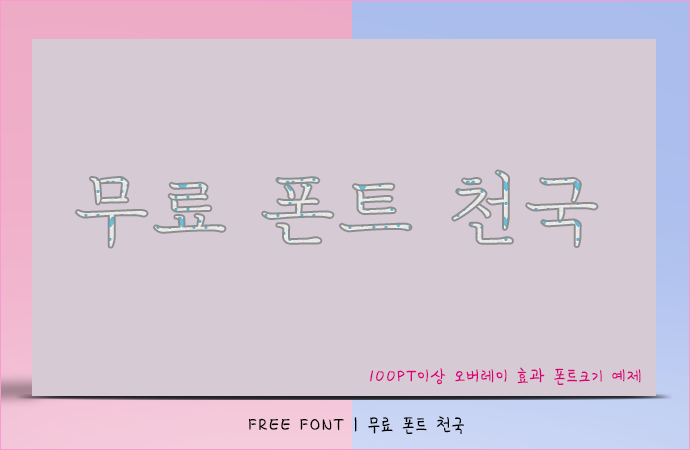
억새풀의 감성이 담겨 있는 마포 꽃섬 한글 폰트
마포 꽃섬 폰트 정보
마포 꽃섬은 난지, 하늘공원의 탁 트인 하늘과 살랑이는 억새풀의 감성적인 인상을 서체로 표현 했습니다. 길게 뻗은 획과 완만하게 구부러진 부리는 부드러운 식물의 줄기를 표현 했으며 획의 두께를 얇게 하고 획순에 따라 끊음으로써 부드럽고 따뜻한 인상을 주고 있습니다. 본 서체는 누구나 자유롭게 사용 가능한 무료 서체입니다.
마포 꽃섬 폰트 # 미리보기
마포 꽃섬, 12~80PT 크기로 가독성을 테스트 해본 폰트
마포 꽃섬, 100PT 크기 이상으로 작업한 오버레이 효과를 적용한 폰트
마포 꽃섬, 100PT 크기 이상으로 그레이언트를 효과를 적용한 폰트